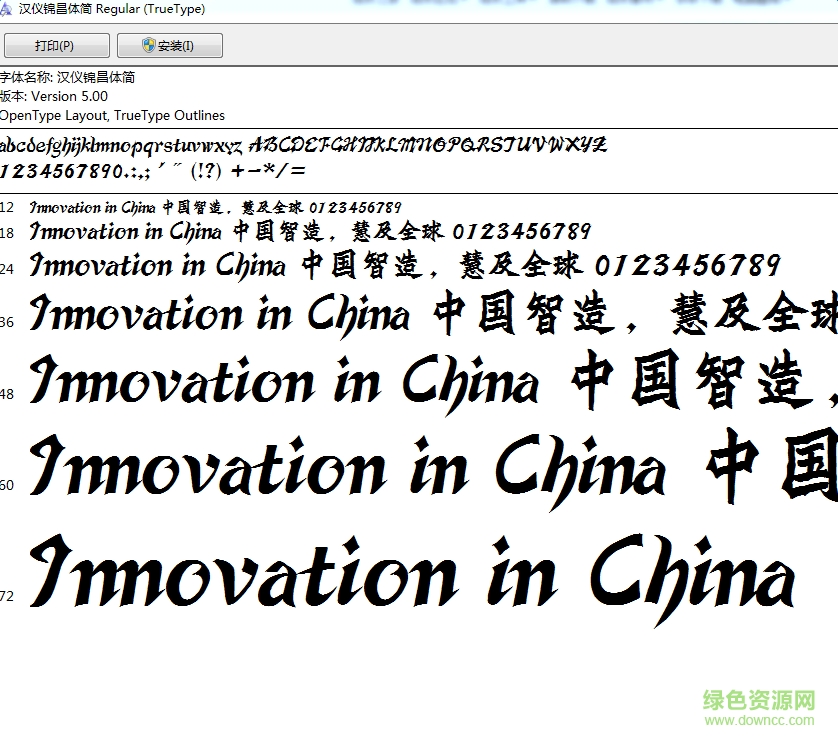
汉仪锦昌体简是一款汉仪类古典文雅风格字体软件,锦昌体一笔一画一丝不苟,粗细相间,优雅气息十足,下面即是字体效果预览图,非常好看!还有更多类似好看字体欢迎来绿色资源网下载体验!
汉仪锦昌体简是一款应用于艺术设计方面的简体中文字体,该字体笔画粗壮,尾部的甩尾有力且有丰富的笔触细节,大字效果突出且引人注目;并且最大程度还原作者书写字形,细节表现完整,且字库完整,可以广泛应用于名片设计、新闻媒体、宣传海报、ppt、影视制作以及内容用字等领域。
该字体横细竖粗,非常的文雅脱俗,整体效果十分酷炫好看,尽显书法大师的魅力,用来耍酷再合适不过了!